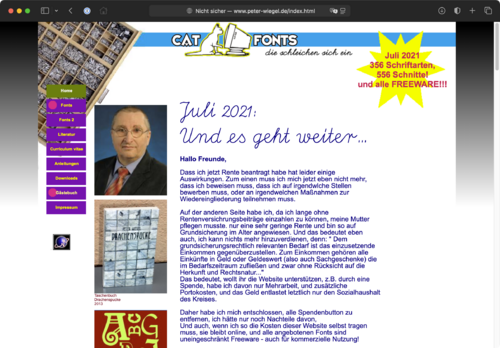
Aktuell sind Peter Wiegels kostenlose Schriften noch über http://www.catfonts.de erreichbar. Für den Fall, dass die Website in Zukunft einmal nicht mehr aufrechterhalten werden kann, ist hier ein Download des gesamten Schriftenwerks hinterlegt. Über 300 Schriftfamilien, in einzelnen Ordnern mit allen Fonts und Beispielbildern. Typografie.info bietet sich dafür insbesondere deshalb an, da ein Großteil der Schriften als Reaktion auf Forendiskussionen entstanden ist.
Eine Digitalisierung der Berthold-Signal-Schriften in drei Schnitten (.OTF) und alternativ als ein variabler Font.
Eine dicktengleiche Schrift, die der Anbieter Frere-Jones für Intel entwickelt hat und die kostenlos unter OFL angeboten wird.
Mona Sans und Hubot Sans sind zwei Groteskfamilien von Deni Anggara für Github, die unter der Open Font License veröffentlich wurden. Die Schriften wurden als variable Fonts entwickelt. Als Einzelschnitte kommt die Mona Sans auf 48, die Hubot Sans auf 64 Schnitte.
Eine kostenlose Schriftfamilie mit lateinischer und kyrillischer Belegung von Dmitry Rastvortsev. Wahlweise nutzbar als variabler Font in drei Varianten (Sans, Serif und Titling) oder in 63 aufrechten Einzelschnitten. Ebenfalls im Paket enthalten sind Piktogramme mit Motiven aus der Stadt Kiew von Olya Kiselova.
Eine umfangreich ausgebaute Digitalisierung der Deutschmeister schmalfett, veröffentlicht unter OFL-Lizenz nach einer Kickstarter-Kampagne. Version A enthält die ursprünglichen Glyphen, die mit den bedingten Ligaturen für traditionellen Fraktursatz eingesetzt werden können. Version B enthält modernisierte Glyphen-Varianten für eine bessere Lesbarkeit und eine internationale Anwendung.
Die Chaumont Script basiert auf dem Schriftstil des französischen Schildermalers Chantal Jacquet. Durch unzählige Varianten und Ligaturen ist der Stil als digitaler Font nutzbar gemacht worden. Die Schrift mit über 2000 Glyphen erschien unter der Open Font License und als Beta-Version bei Atelier National de Recherche Typographique.
FDI Altmeister A und B. Alle Details:
Eine sorgfältige und vollständige, über Kickstarter finanzierte Digitalisierung der Wiking-Schrift der Gießerei J.D. Trennert & Sohn (1925).
Zeichenbelegung: Lateinisch (westeuropäisch, osteuropäisch und zentraleuropäisch).
Traditioneller Fraktursatz mit allen Ligaturen und als Varianten hinterlegten historischen Zeichenformen ist über die OpenType-Funktionen »bedingte Ligaturen« und »Stilsatz 1« möglich.
Eine Schriftdigitalisierung auf Basis spanischer Buchdrucktypen des Druckers Joaquín Ibarra, der damit Don Quijote setzte.
Die Schrift ist quelloffen, unter OFL lizenziert und verfügt in den derzeit generierten Schnitten über drei Strichstärken mit echten Kursiven.
Die D-DIN ist die Hausschrift von Datto Inc. und wurde unter OFL-Lizenz freigegebenen. Die Familie besitzt 8 Schnitte: zwei Weiten (standard und weit) sind in normal, kursiv und fett ausgebaut. Die schmale Weite besitzt zwei Schnitte (normal und fett). Die Zeichenbelegung entspricht mit einigen Abstrichen der einfachen westeuropäischen Belegung.
Die Faune stammt von der französischen Designerin Alice Savoie und wurde vom Centre National des Arts Plastiques in Auftrag gegeben.
Die Familie besteht aus drei Text- und drei Displayschnitten.
Die Poppins ist eine geometrische Groteskfamilie, die das lateinische Schriftsystem und Devanagari unterstützt.
Die Familie verfügt über neun Strichtstärken mit zugehörigen Kursivschnitten.
Die Antiqua-Familie aus der IBM-Plex-Superfamilie. 8 Strichstärken mit Kursiven.
Die Sans-Familie aus der IBM-Plex-Superfamilie. 8 Strichstärken mit Kursiven.
Die Monospaced-Familie aus der IBM-Plex-Superfamilie. 8 Strichstärken mit Kursiven.
Zilla Slab ist eine von Typotheque für Mozilla entwickelte Open-Source-Schriftfamilie. Die Schrift besteht aus sechs Strichstärken mit Kursiven sowie zwei negativen Schnitten.
Die Bungee von David Jonathan Ross wurde speziell für den vertikalen Satz, wie er etwa an Häuserfronten benutzt wird, ausgelegt. Daneben lässt sich das Versal-Alphabet aber natürlich auch für normalen horizontalen Satz benutzen und verfügt zudem über verschiedene Einzelfonts zum Kombinieren und Erstellen von 3D-Effekten.
Die Cardo von David Perry ist eine traditionelle Renaissance-Antiqua-Schrift, die sich gestalterisch an die Bembo anlehnt. Ihr großer Zeichenvorrat von derzeit über 3800 Zeichen ist auf eine Anwendung in wissenschaftlichen Texten ausgelegt. So enthält die Cardo unter anderem Zeichen für altgriechische Musiknotation, Hebräisch, phonetische Alphabete, Etruskisch, Mittelhochdeutsch, verschiedene Maß- und Gewichtssysteme sowie eine große Zahl an Ligaturen.
Derzeit gibt es die Schrift in drei Schnitten: normal, kursiv und fett.